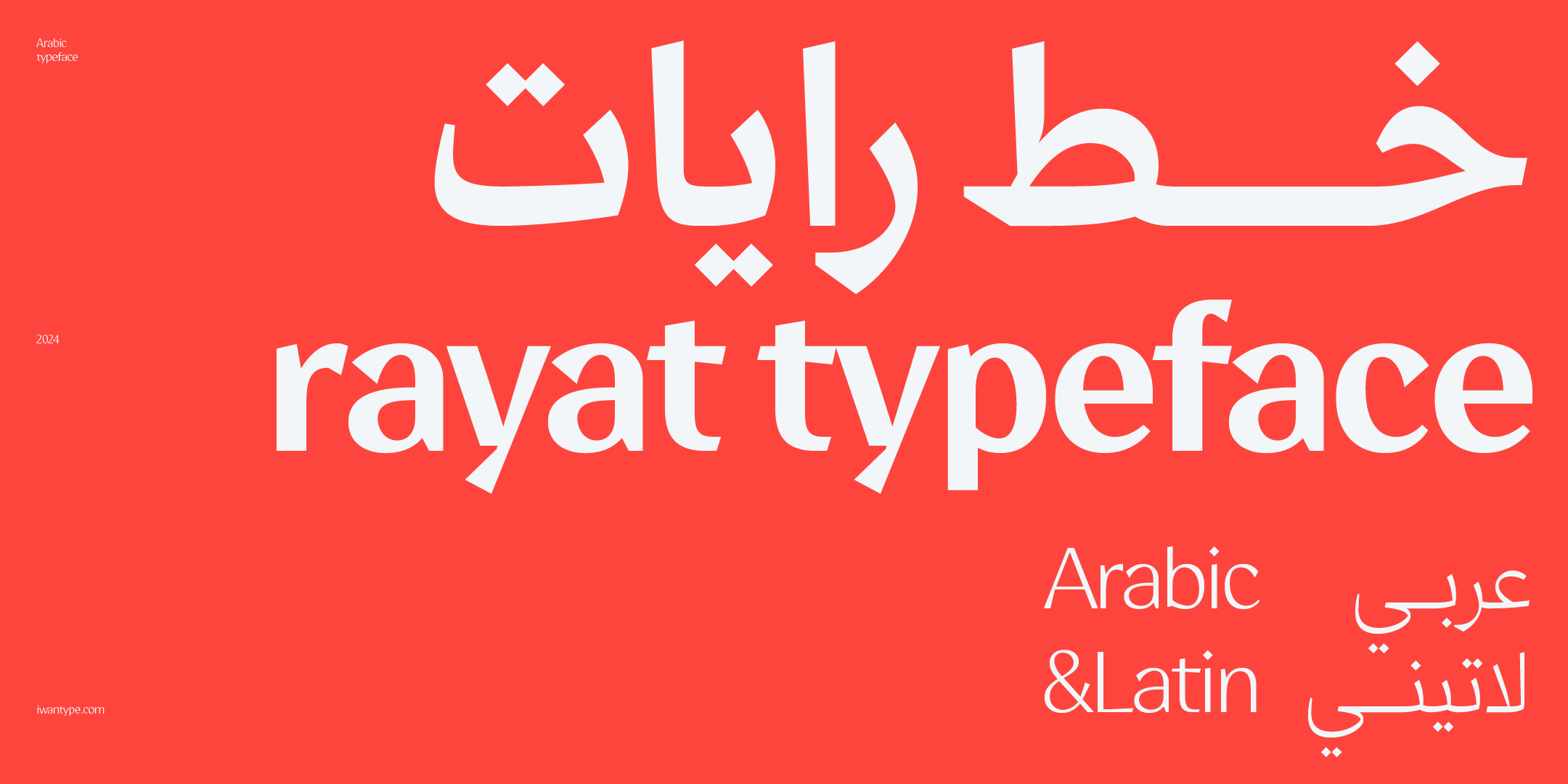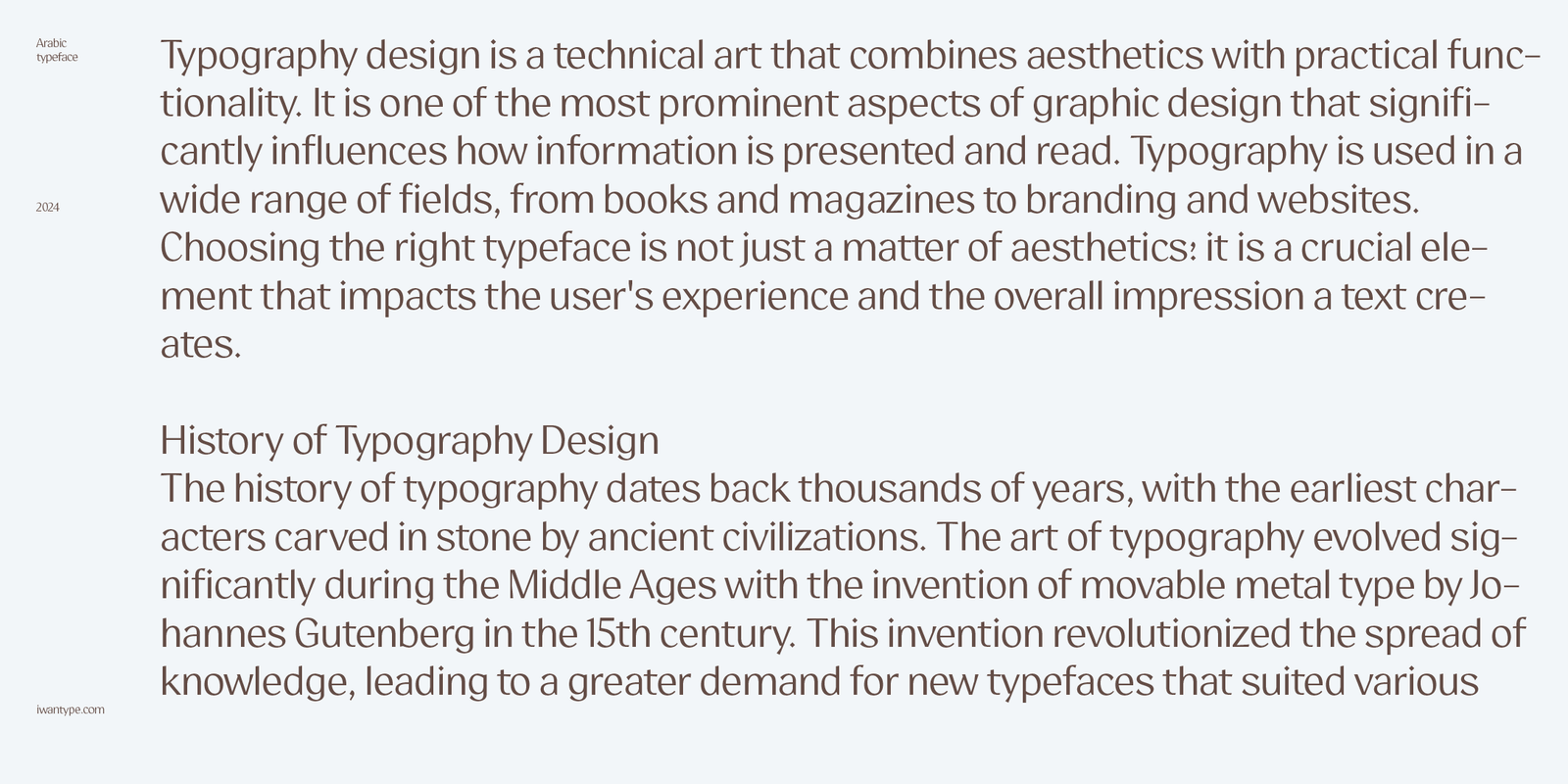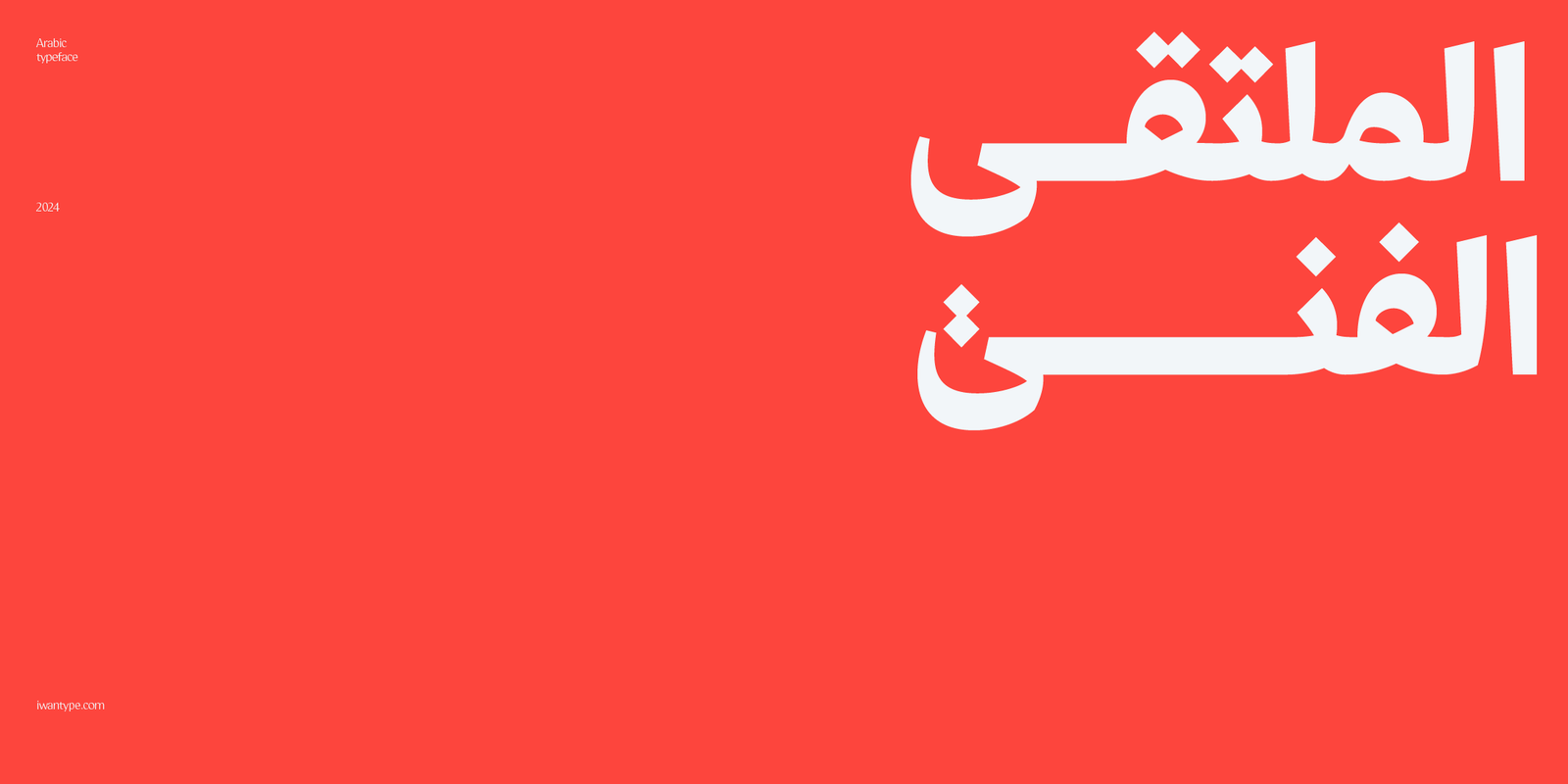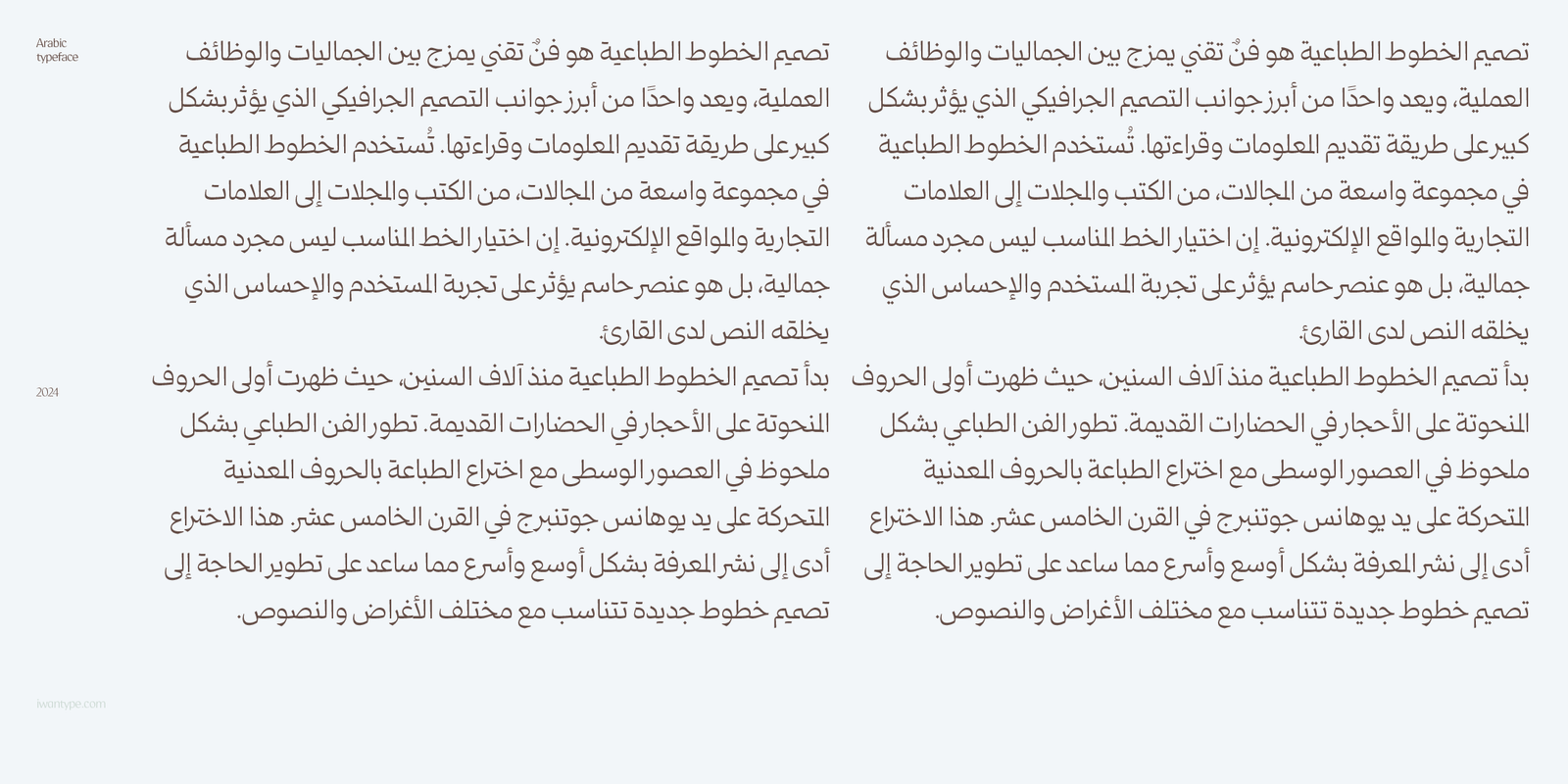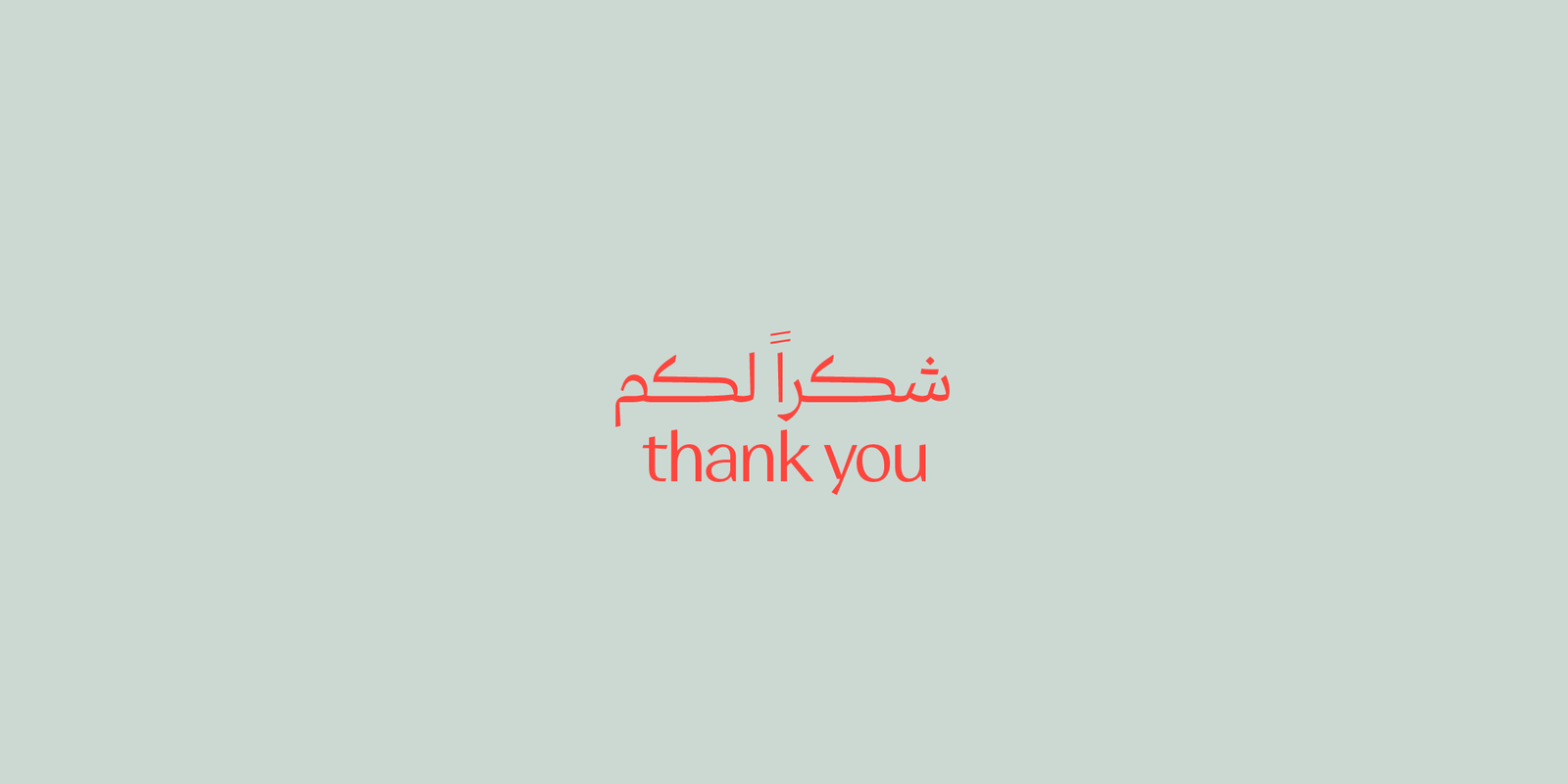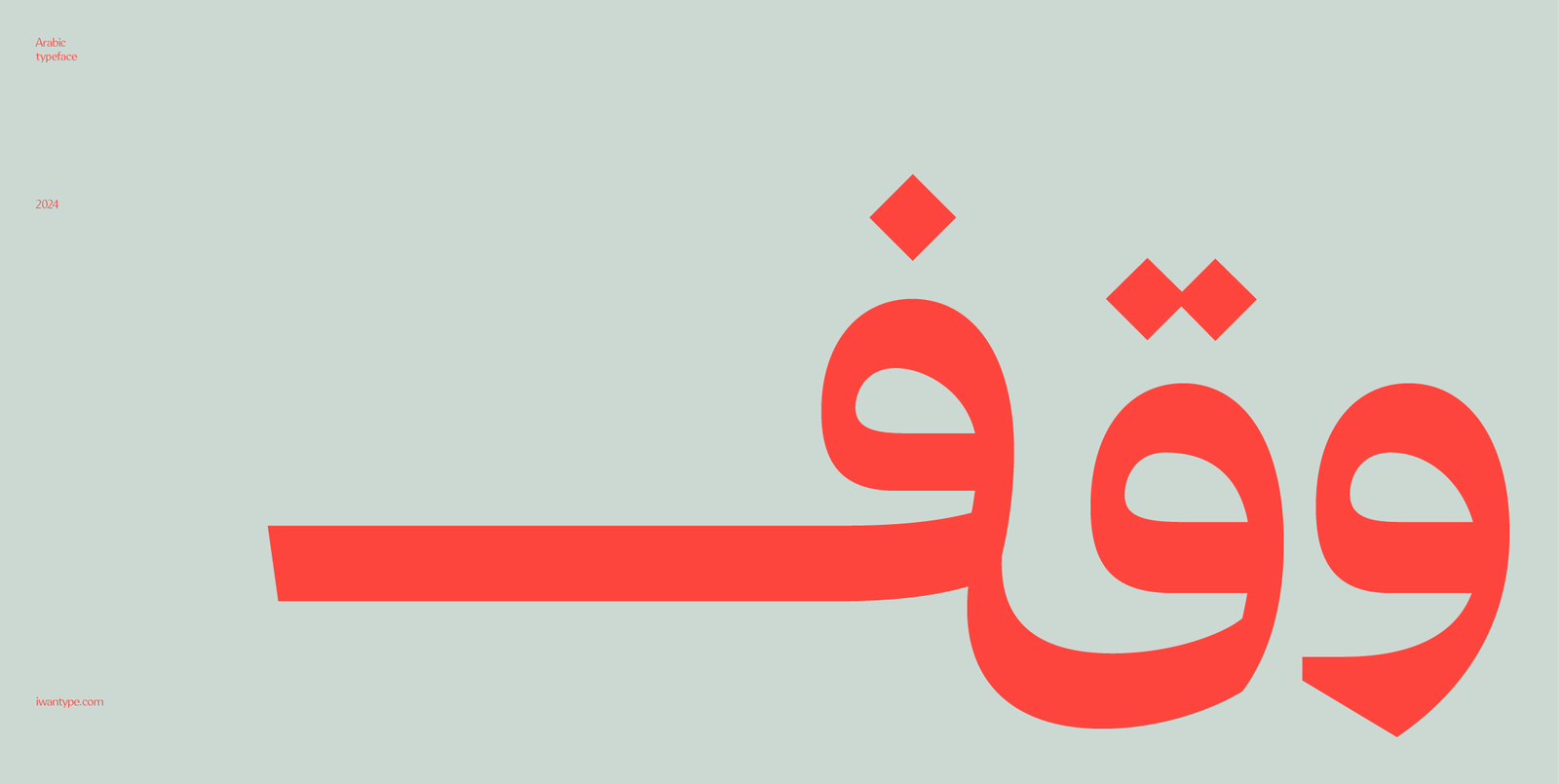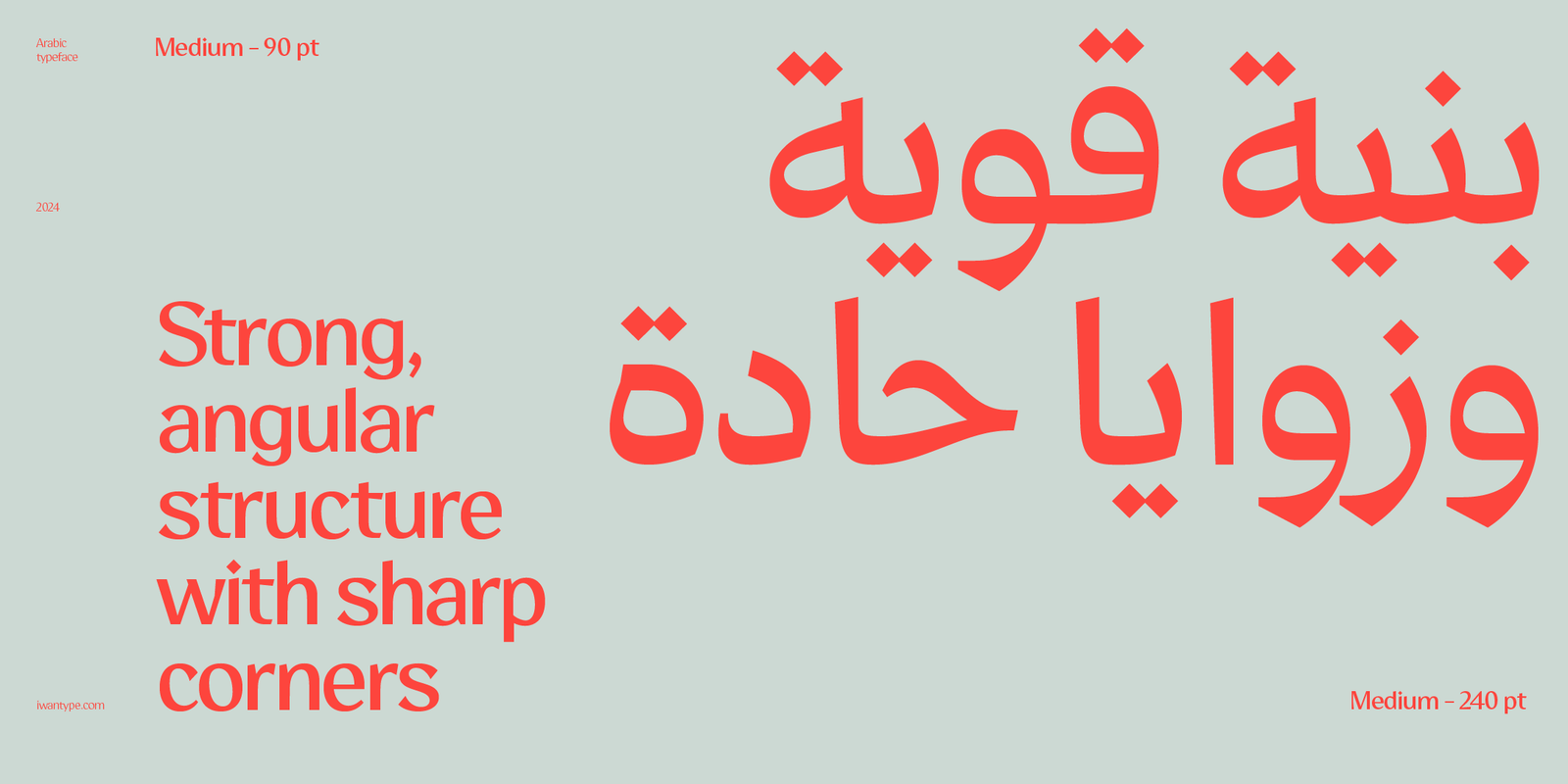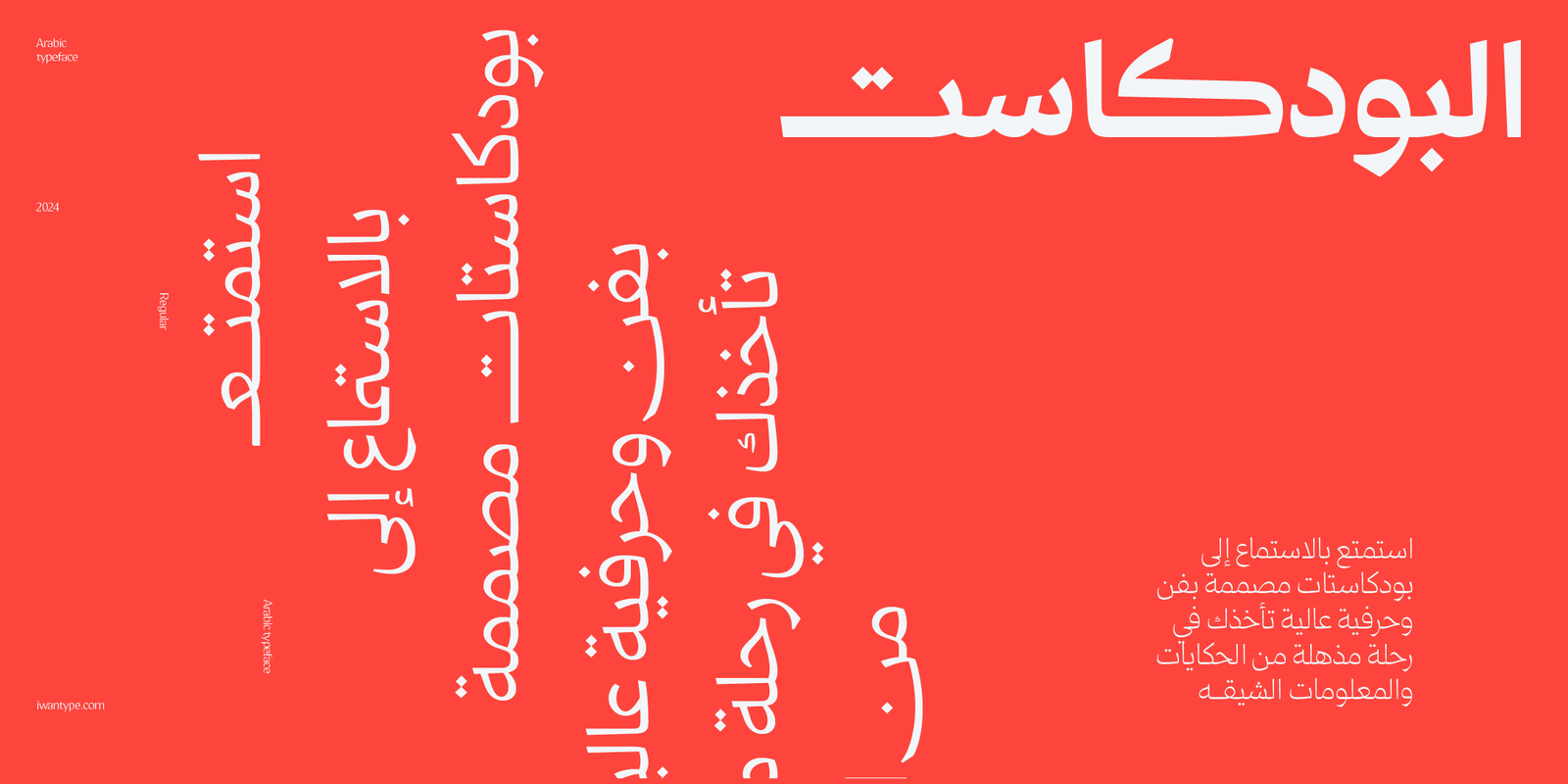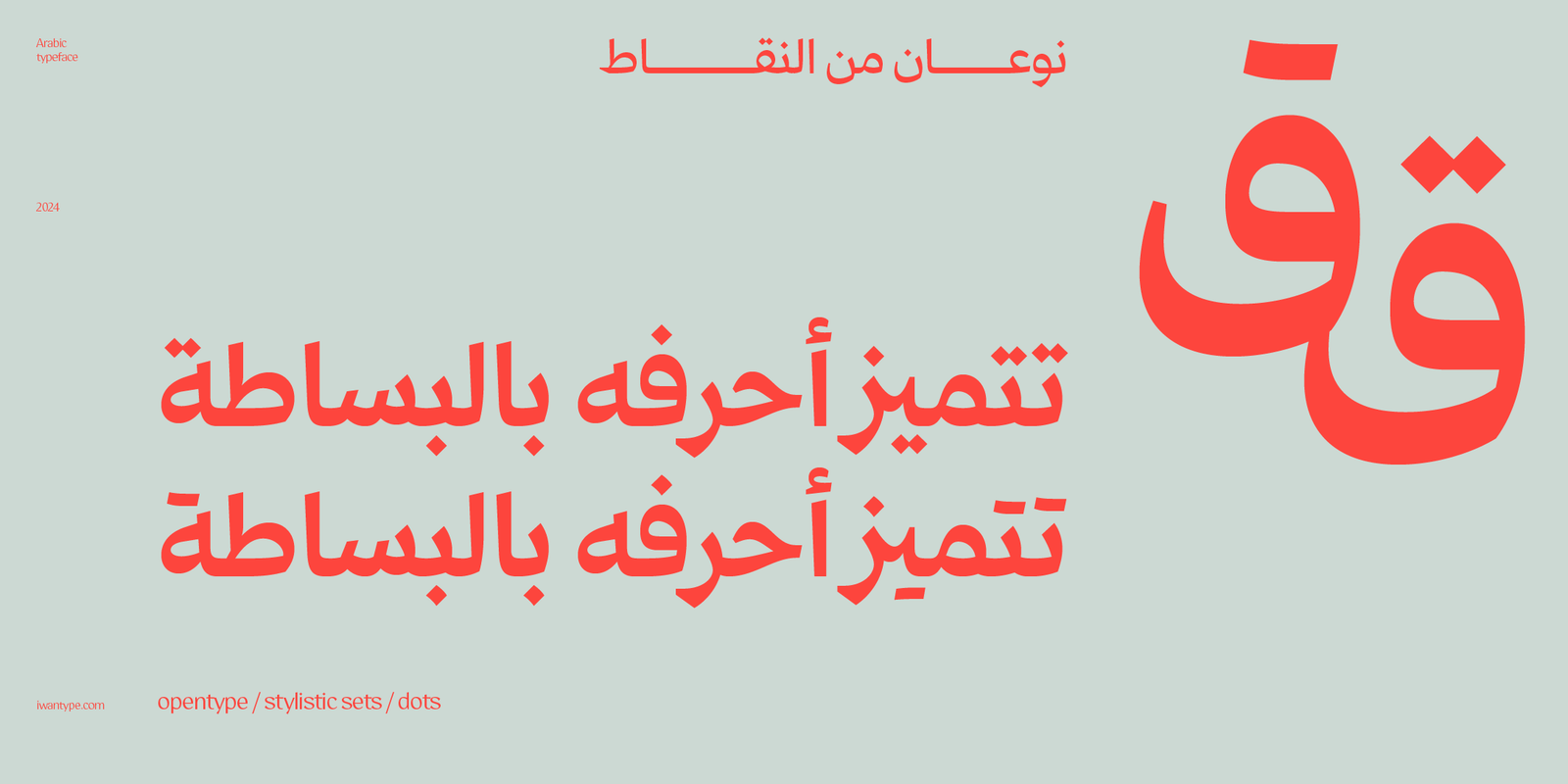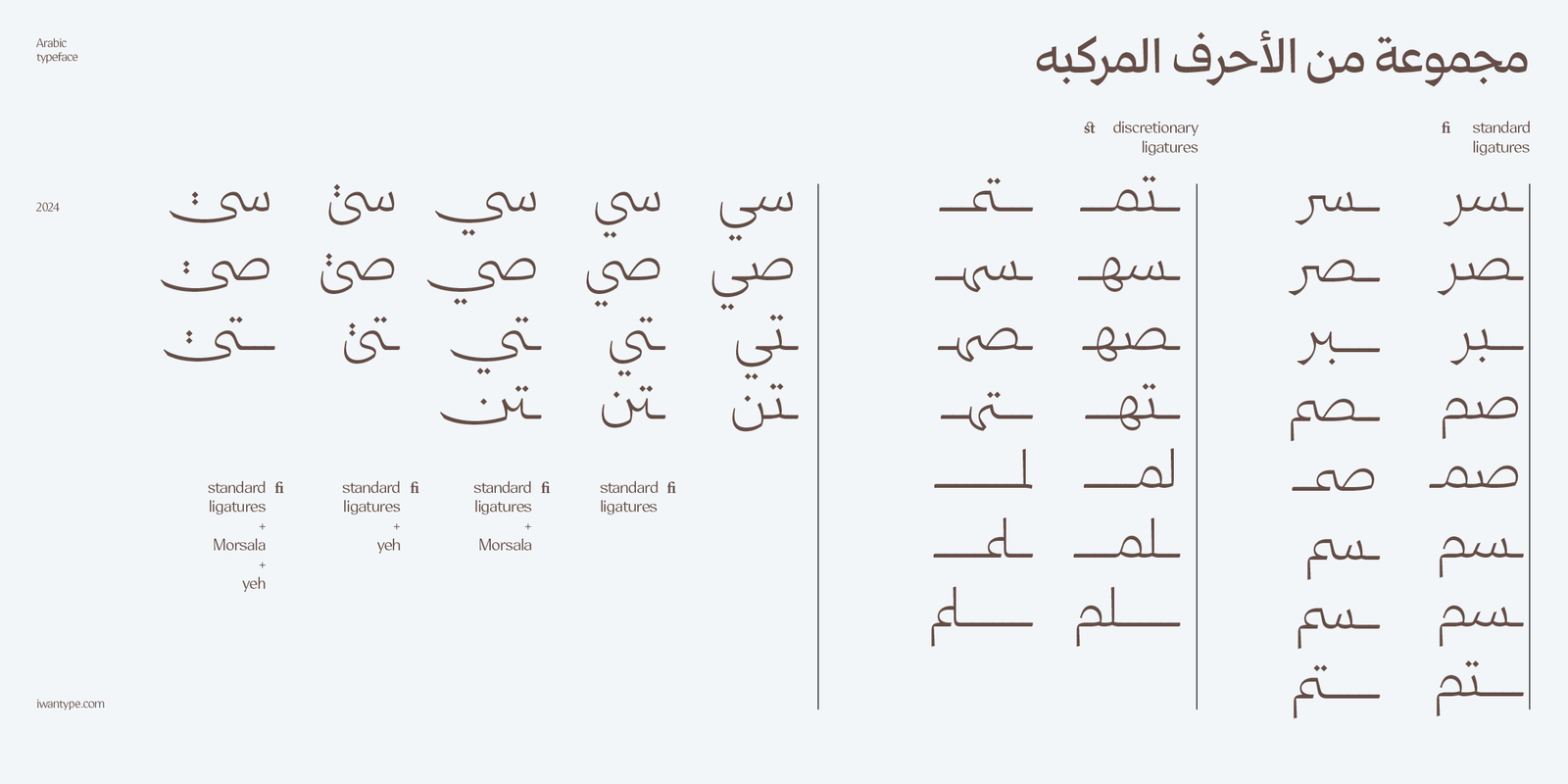
خط رايات الطباعي – خط نسخ – Rayat Arabic typeface
خط “رايات” هو خط نسخ عربي حديث يتميز ببنية قوية وزوايا حادة تمنحه طابعًا جريئًا ومميزًا في الهوية البصرية. يتميز الخط بمساحات تجويف داخلي (Counter Space) واسعة، مما يعزز وضوح الحروف ويضفي راحة بصرية عند القراءة، خاصة في الأحجام الكبيرة. يدعم خط “رايات” اللغات العربية واللاتينية، مما يجعله خيارًا متعدد الاستخدامات يمكن اعتماده في المشاريع التي تتطلب توافقًا بين النصوص العربية واللاتينية.
يعد هذا الخط مناسبًا للتصميمات التي تحتاج إلى جاذبية بصرية وقوة تعبيرية، سواء في العناوين البارزة أو العلامات التجارية. يجمع “رايات” بين الأصالة والجمال الهندسي ليكون خيارًا مثاليًا للمصممين الذين يبحثون عن طابع عصري وقوي في تصاميمهم.
مميزات خط رايات الطباعي:
- أحرف مرسلة (تُفعَّل بإضافة “ءء” بعد الحرف)
- حرف ياء بنزول أقل: يقلل من نزول السطر، مما يعزز من انتظام النصوص.
- أحرف المركبة: تسهم في تحسين المظهر العام للنص وتزيد من سلاسته.
- نقاط بديلة
- يدعم رمز الريال السعودي، ويمكن تفعيله بإضافة حرف “ء” بعد كتابة كلمة “ريال”.